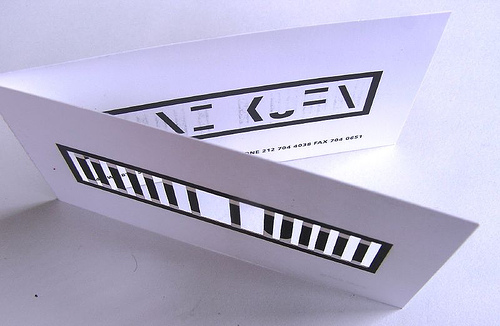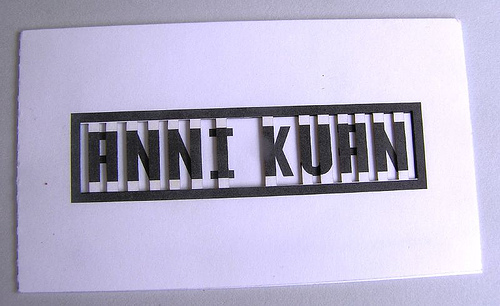
Schrift von ANNI KUAN
Ich suche ebenfalls dringend eine Schrift, und zwar die vom Anni Kuan Logo:
hat jemand vielleicht eine Ahnung um welche Schriftart es hierbei handelt???
zum Beispiel?
ein font mit so einem "A" habe ich bisher noch nicht gefunden!
das logo wurde von sagmeister erstellt und dürfte handgeschnitzt sein :!:
klar, auf irgendeiner schrift wird er aufgebaut haben. das er gleich daraus nen font entwickelt hat, halte ich für abwägig. :roll:
Eine Schrift so zu verunstalten zähle ich zu den gesammelten Grausamkeiten.
das logo ist etwas aus dem kontext gerissen. hier wird es deutlicher warum es aussieht wie es aussieht. :D
Wow! Danke für die vielen Beiträge! Die Visitenkarte hat auch richtig Klasse .... aber ein Logo nur auf das Konzept einer Visitenkarte aufzubauen halt ich für nicht wirklich sinnvoll, oder? Wobei ich das Logo auch für gelungen halte... und nicht für verunstaltet.. aber gut das ist wohl Geschmacksache...